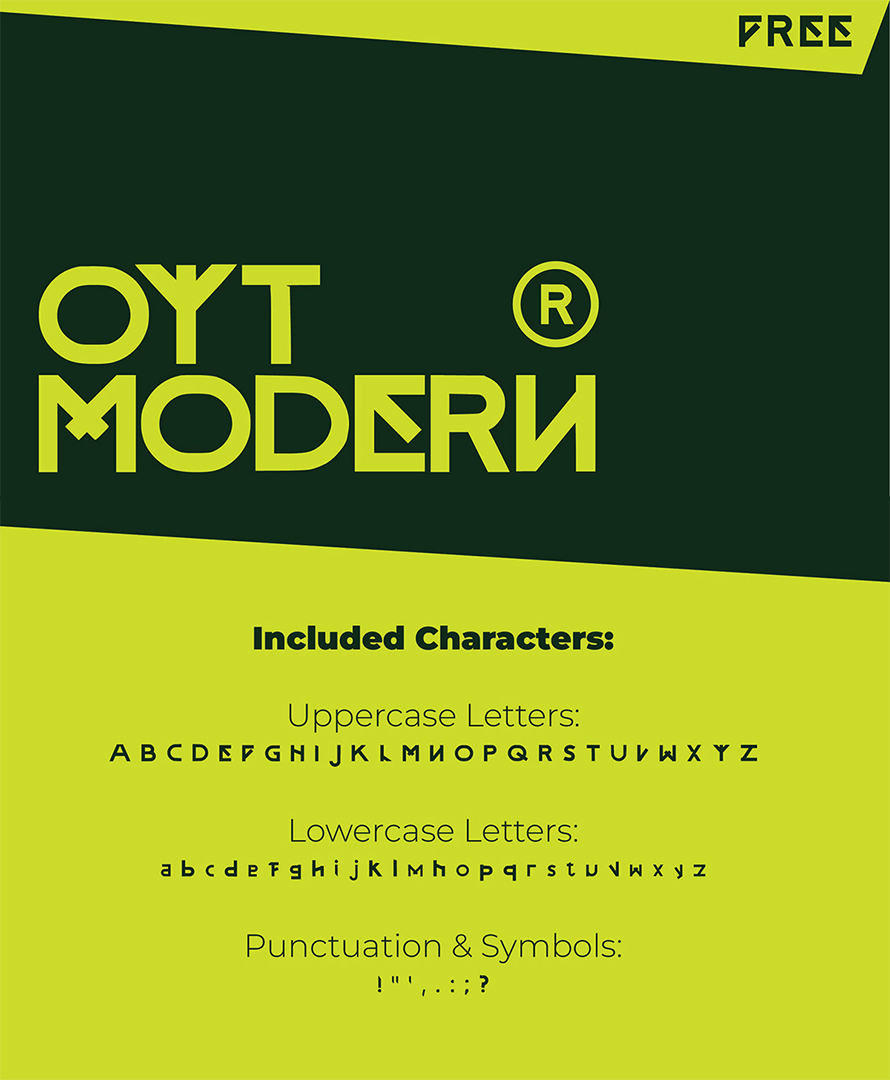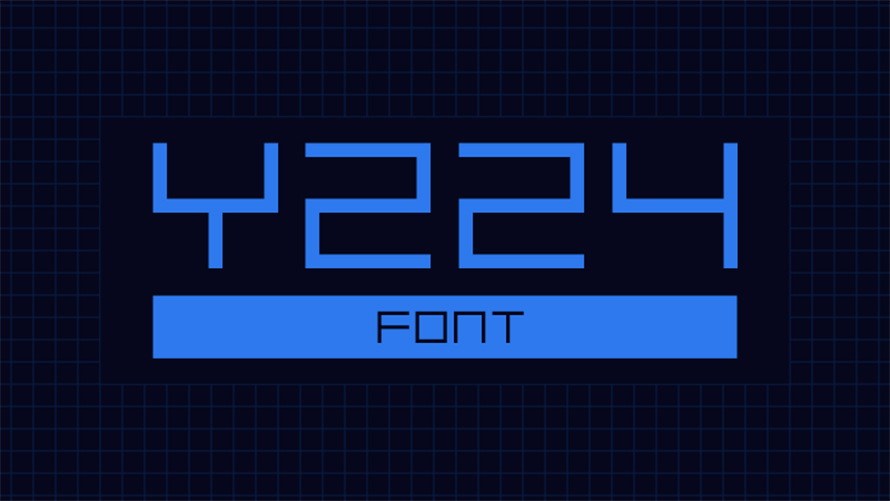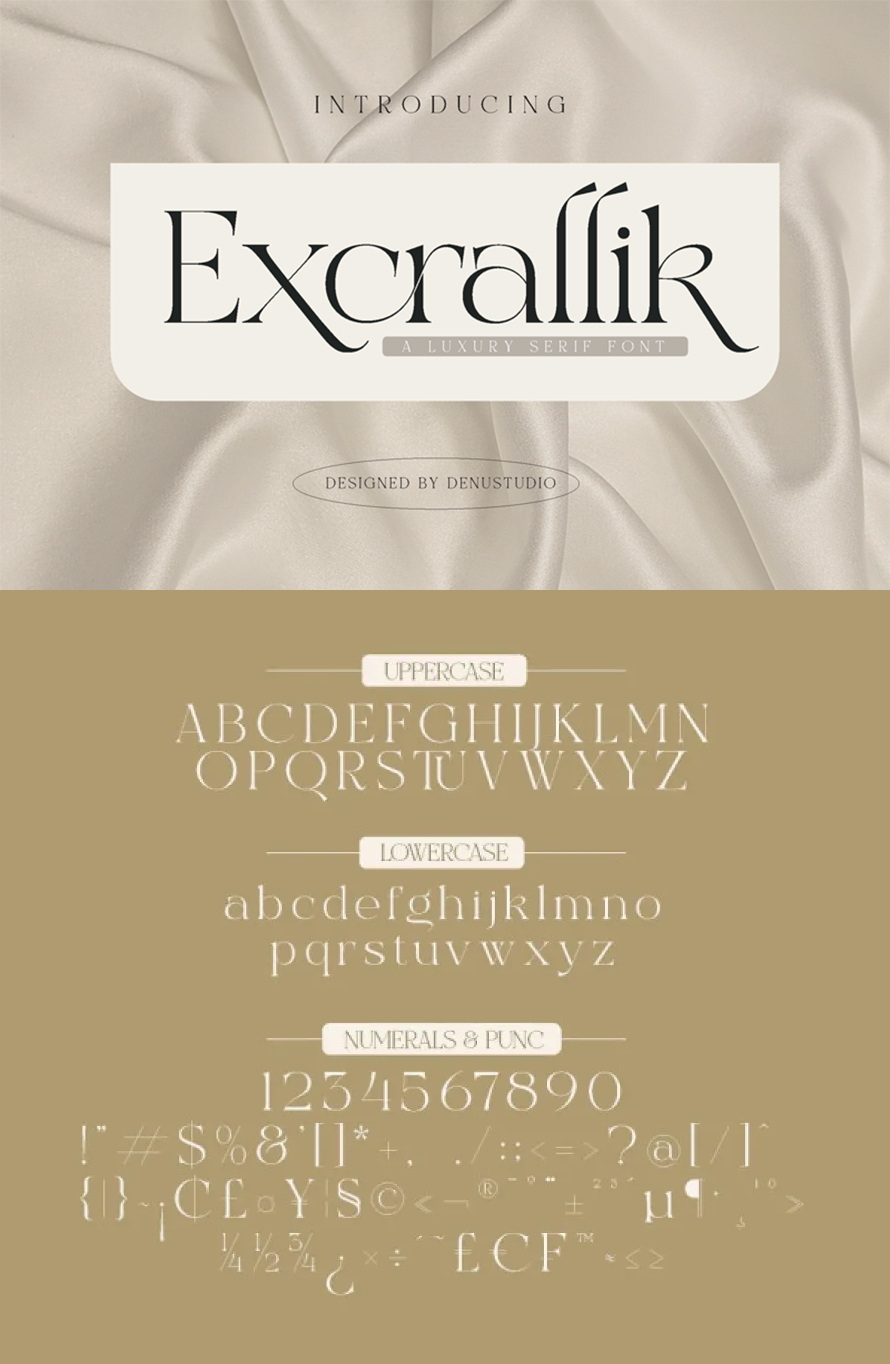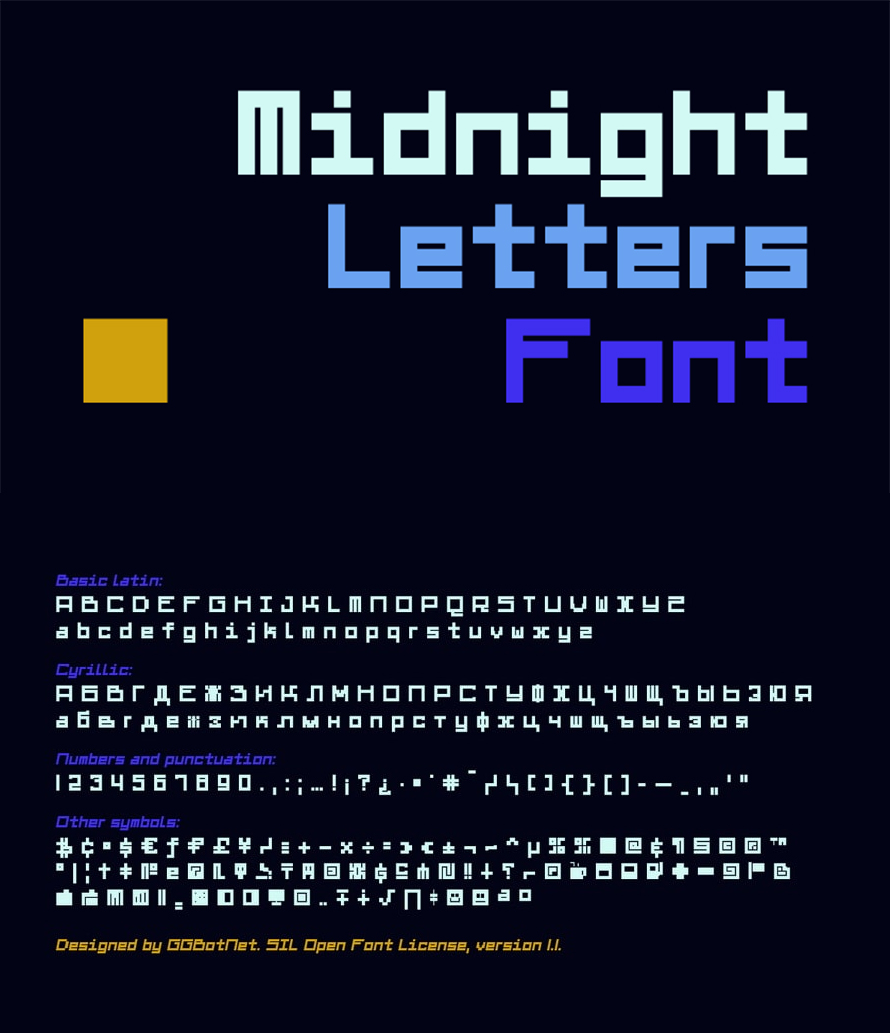
New Fresh Free Fonts
25 neue und frische Fonts für Grafik & Web Designers
Kostenlose Schriftarten sind für jeden Designer unerlässlich, sei es bei der Arbeit an Marken, Websites oder Social-Media-Grafiken. Es kann eine Herausforderung sein, hochwertige kostenlose Schriftarten zu finden, die sowohl stilvoll als auch funktional sind, aber mit der richtigen Sammlung können Sie Ihre Designs mühelos aufwerten. Typografie spielt eine entscheidende Rolle bei der Erstellung von visuell ansprechendem Inhalt, und neue Schriftarten-Veröffentlichungen bieten innovative Stile, die mit modernen Designtrends übereinstimmen. Von kräftigen Display-Schriften bis hin zu eleganten Skripten können kostenlose Schriftarten ein gewöhnliches Projekt in ein atemberaubendes Meisterwerk verwandeln, während sie einen professionellen Touch bewahren. Entdecken Sie die neuesten Typografie-Optionen, um Ihre kreative Arbeit zu verbessern.
Moderne Schriftgestaltung und Typografie entwickeln sich ständig weiter, da Designer nach frischen und einzigartigen Schriftarten suchen. Neue kostenlose Schriftarten führen zeitgemäße Stile ein, die mit aufkommenden Trends wie Minimalismus, futuristischem Design und dynamischer Schriftgestaltung in Einklang stehen. Diese Schriftarten bieten Vielseitigkeit, sodass Grafik- und Webdesigner ansprechende Benutzeroberflächen, auffällige Markenmaterialien und ästhetisch ansprechende digitale Erlebnisse schaffen können. Mit der zunehmenden Nachfrage nach Originalität bieten kostenlose Schriftarten eine zugängliche Möglichkeit, mit neuen Stilen zu experimentieren, ohne das Budget zu sprengen.
Liste der neuen frischen kostenlosen Schriftarten
Neue frische kostenlose Schriftarten für Grafik- und Webdesigner
Wenn du nach den neuesten und stilvollsten modernen Schriftarten suchst, ist unsere handverlesene Auswahl an frischen kostenlosen Schriftarten genau das Richtige für dich. Egal, ob du moderne serifenlose Schriftarten für ein sauberes Website-Layout oder ein dekoratives Skript für Branding benötigst, diese Schriftarten verleihen deinen Designs das gewisse Etwas. Wir haben diese Sammlung sorgfältig zusammengestellt, um dir zu helfen, in der Designwelt einen Schritt voraus zu bleiben. Entdecke die Liste und lade deine Favoriten herunter, um deinen Projekten einen professionellen und kreativen Vorteil zu verschaffen.
Redland Free Font
Lade Redland herunter, eine zeitlose Serifenschrift, die perfekt ist, um eine starke Marke oder ein Logo zu erstellen. Ihre eleganten Kurven werden sicher deine Aufmerksamkeit auf sich ziehen, während sie eine raffinierte Persönlichkeit bewahrt. Mit mehreren Gewichten, stilistischen Ligaturen und alternativen Schriftarten ist Redland eine vielseitige Option für jedes Designprojekt. Und das Beste daran: Sie ist völlig kostenlos herunterladbar. Verpasse nicht die Gelegenheit, dein Design mit Redland zu verbessern.
Oyt Free Font
OYT ist eine moderne, durchdacht gestaltete Schrift, die sich von Einfachheit, Minimalismus und der Schönheit des Zufalls inspirieren lässt. Sie wurde entwickelt, um eine saubere Struktur mit einem organischen, mühelosen Fluss zu verbinden und dabei eine zurückhaltende, aber ausdrucksstarke Persönlichkeit zu bewahren. Ob für Branding, redaktionelle Layouts, digitale Designs oder kreative Projekte – OYT passt sich nahtlos an und bietet eine raffinierte und dennoch ungebremste Ästhetik.
Elysia Free Font
Hol dir Elysia, die moderne Schrift, die sich von vintage-neogotischen Schriftzügen inspirieren lässt. Diese vielseitige Schrift hat eine doppelte Persönlichkeit und eignet sich perfekt für verschiedene Projekte wie Hochzeitseinladungen, Branding, Magazin-Illustrationen und mehr. Und das Beste daran? Du kannst Elysia kostenlos herunterladen! Verpasse nicht die Chance, deinem nächsten Projekt Spaß und Persönlichkeit zu verleihen.
Y224 Free Font
Kostenlose Schriftarten sind Schriftarten, die ohne Kosten für die private oder kommerzielle Nutzung zur Verfügung stehen. Sie gibt es in verschiedenen Stilen, von eleganten Scripts bis hin zu kräftigen Display-Schriften. Viele Designer nutzen kostenlose Schriftarten, um ihre Kreativität zu steigern und gleichzeitig Geld zu sparen. Websites wie Google Fonts und DaFont bieten umfangreiche Bibliotheken, die für alle Projekte Zugang und Vielfalt gewährleisten.
Geuli Free Font
Geuli ist eine coole, moderne und minimalistische Display-Schrift. Diese Schrift eignet sich ideal für Webdesigns, Visitenkarten oder fast alles, was eine einzigartige Note benötigt.
Midnight Letters Free Font
Eine kostenlose Schriftart ist eine Schrift, die kostenlos heruntergeladen und verwendet werden kann. Diese Schriftarten werden oft von Designern geteilt oder auf Open-Source-Plattformen gefunden, die es Einzelpersonen ermöglichen, ihre Projekte ohne finanzielle Einschränkungen zu personalisieren. Sie bieten eine Vielzahl von Stilen, die kreative Freiheit und Vielseitigkeit im Design ermöglichen.
Magnetar Free Font
Die beste Schriftart hängt von ihrem Zweck ab. Für Lesbarkeit sind serifenlose Schriftarten wie Helvetica hervorragend. Für Eleganz glänzen Serifenschriften wie Garamond. Eine großartige Schriftart balanciert Ästhetik, Lesbarkeit und Vielseitigkeit.
Excrallik Free Font